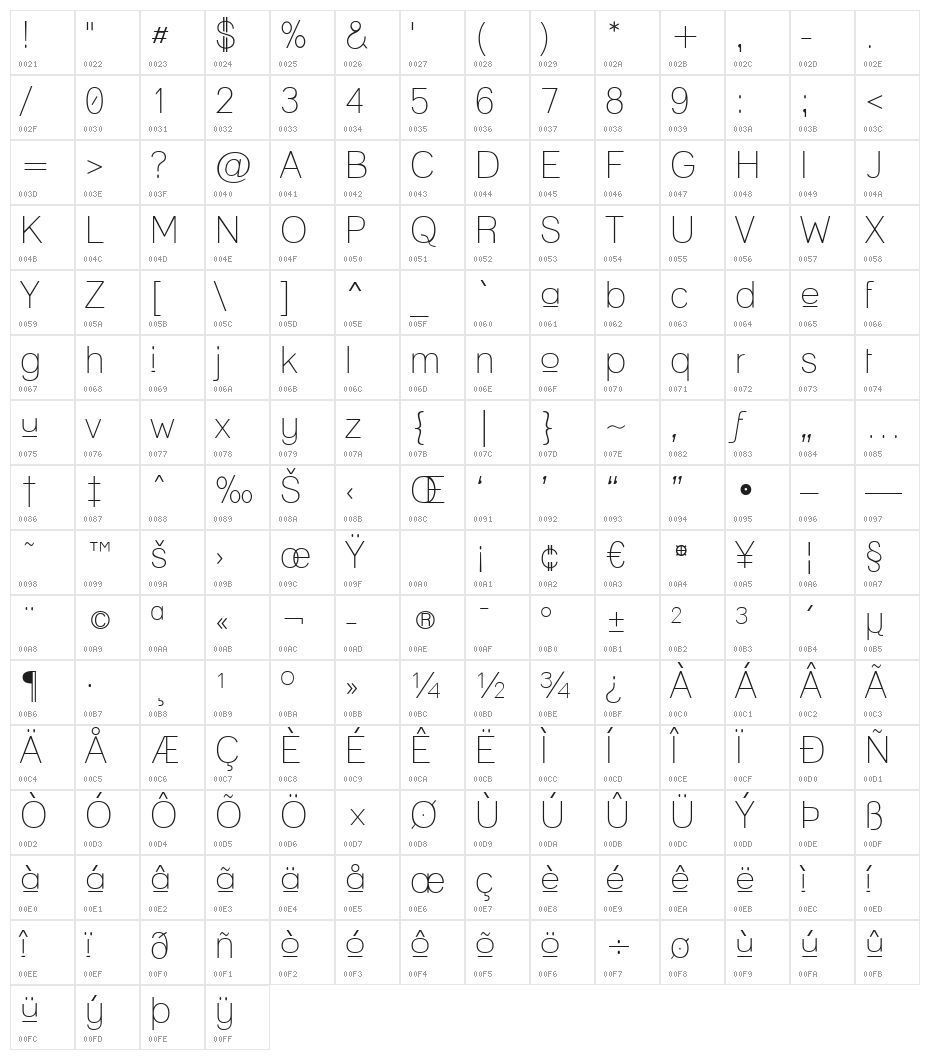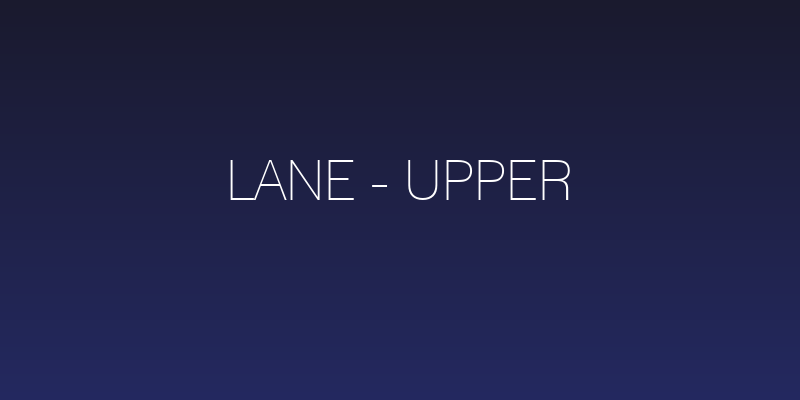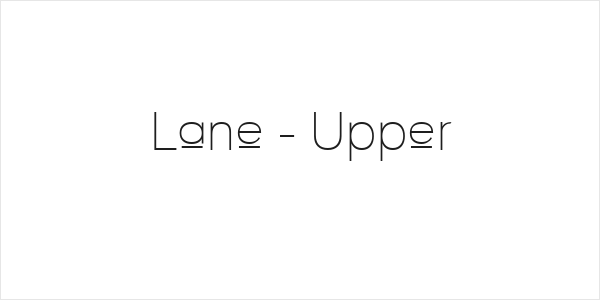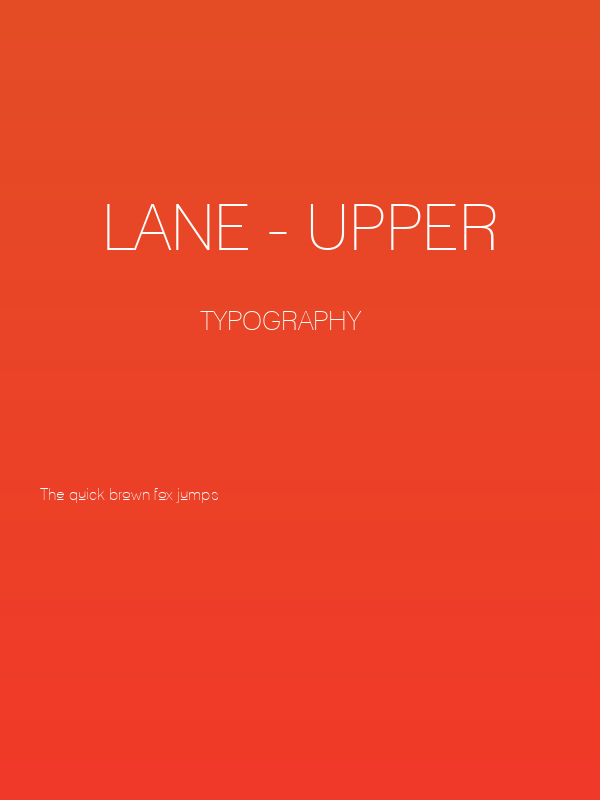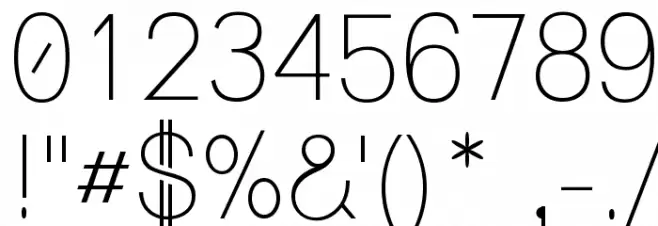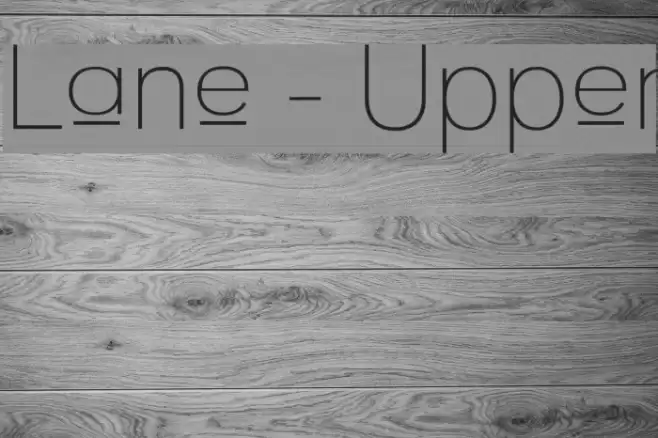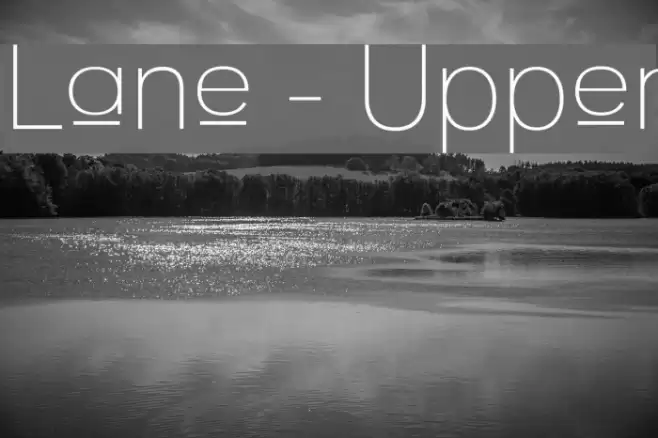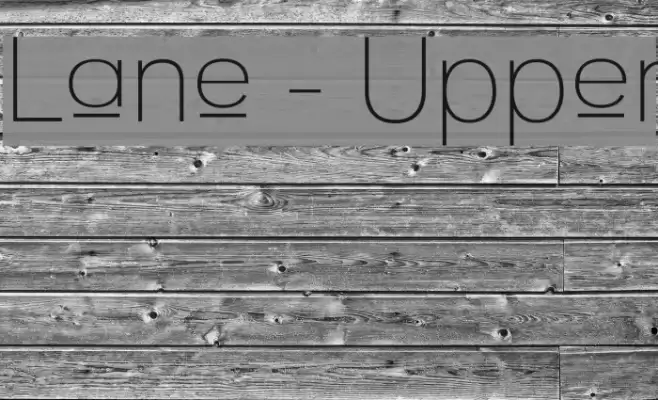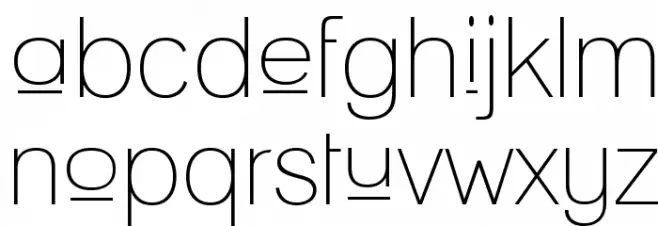
Lane - Upper Font
| Projetos propostos | Ideal for branding, advertising, web design, and editorial projects where clarity and modernity are essential. |